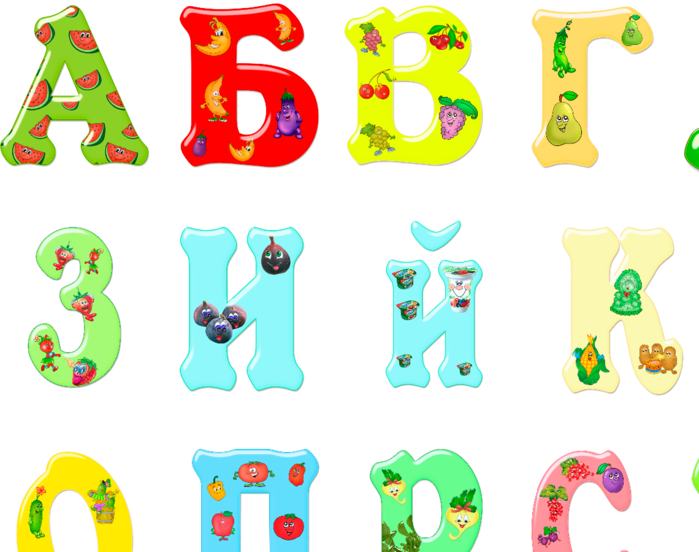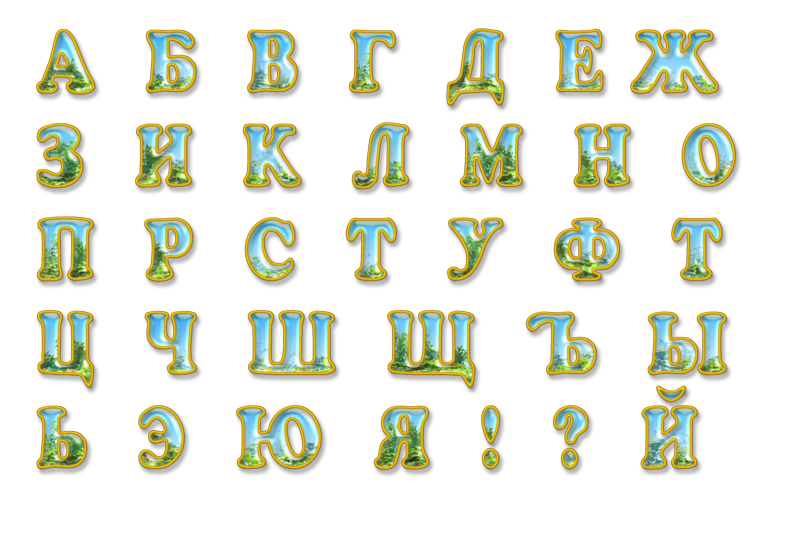
Создание красивого текста. MS Office Word 2007. WordArt.
Безусловно, на сегодняшний день MS Office Word — популярнейший редактор для создания текстов. Однако Word все-таки остается офисным приложением. Все имеющиеся по умолчанию шрифты предназначены для документов. Впрочем, разработчики Microsoft не оставили пользователей своего продукта в беде – с помощью MS Office Word можно создать действительно красивый текст.
WordArt представляет собой специальный инструмент, преобразующий введенный текст в картинку. Вы сможете менять фон этой картинки, объем, положение на экране. В общем, с помощью WordArt у Вас получится создать действительно красивую надпись за пару минут.
В нём Вы можете задать шрифт, размер, жирность или курсив. Поэкспериментируйте и выберите, что Вам больше понравится. Просто введите текст и нажмите ОК.
Например, мы решили сделать заголовок открытки для стенгазеты.
Здесь Вы можете изменить макет текста-картинки, заливку, контур, положение букв, убрать или добавить тень, изменить объем – в общем, выбрать нужный вариант оформления. Например, мы решили изменить положение текста на экране. Для этого мы выбираем пункт Изменить фигуру (рис.6).
В итоге мы решили выбрать положение текста «Волна 1» и убрать тень. Для этого в эффектах тени (см.рис.6) мы выбрали пункт «Нет тени«. Результат редактирования объекта WordArt представлен на рис.7.
Красивый заголовок для поздравления готов, осталось придумать текст!
Существует множество хитростей, которые помогут вам быстро сделать стенгазету с красивой надписью «С Новым годом!». Нарисовать надпись зачастую бывает сложнее всего, и поэтому мы предлагаем начать именно с нее! Если вы не относитесь к гениям каллиграфии, можно освоить тот или иной шрифт буквально за пару часов. Тем более, что вам только и надо, что сделать одну-единственную надпись!
Найдите в интернете надпись «С Новым годом!», написанную понравившимся шрифтом или напишите ее сами в текстовом редакторе. Затем попробуйте скопировать ее. Сделать это можно, глядя на монитор, или распечатав на принтере и положив сверху кальку. Но научиться делать нужные завитки не достаточно. Порой довольно трудно изобразить объект или фразу в больших масштабах, а стенгазета требует именно этого.
Предлагаем вам несколько вариантов красивых надписей «С Новым годом!», которые можно дополнительно украсить блестками, стразами и бантиками.
На втором месте по легкости изображения форм стоит новогодняя елочка . Предлагаем вашему вниманию несколько вариантов изображений, которые могут украсить любые, даже маленькие плакаты на Новый год !
Полезный совет: одно из основных правил, как рисовать новогоднюю стенгазету заключается в крупных формах.
Не стоит делать множество мелких изображений, чтобы издалека ваша работа смотрелась ярко и отчетливо, а не сливалась в пестрое пятно.
Елочные шары тоже могут стать основной тематической формой на вашей стенгазете. Круг — самая простая и совершенная форма, а разнообразить ее можно бесчисленными способами.
Как украсить изображения елочных шариков:
- Используйте различные орнаменты. Это один из самых простых и быстрых способов сделать красивый рисунок.
- Посыпьте блестками.
- Приклейте настоящие бантики.
- Сделайте коллаж, приклеив на шарики бусины, стразы, кусочки материи и т.д.
Перечень легких рисунков на Новый год продолжает еловая веточка. Ветвь состоит из основы и иголок, кое-где можно изобразить шишки.
, «Тень»
, «Отражение»
, «Свечение»
А теперь давайте разберемся, что еще используется, для красивого оформления напечатанных в блоке слов.